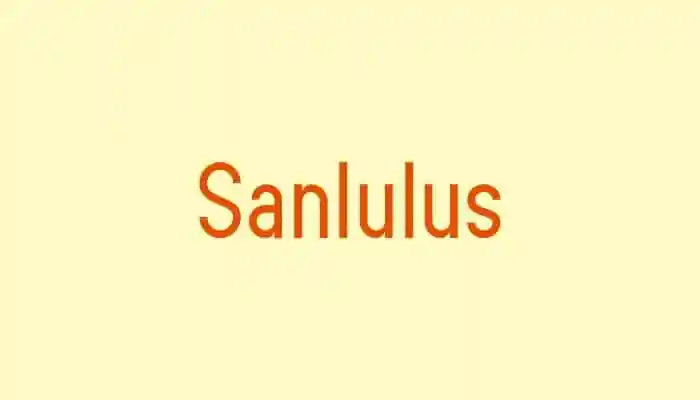
Sanlulus Sans Serif é uma fonte moderna e clean que oferece um toque industrial distintivo sem perder sua simplicidade pura. Suas linhas leves e a arquitetura neutra permitem uma ampla gama de possibilidades para qualquer aplicação visual, seja como logomarca, headlines impactantes, títulos expressivos, capas de revistas ou até mesmo cartazes que desejam fazer um forte impacto. Ideal para os designers que buscam uma fonte sólida e versátil, Sanlulus se torna a escolha perfeita para qualquer projeto que precise expressar determinação e força visualmente. Suave mas inegavelmente aguerrido, esta é uma adição valiosa ao seu arsenal de recursos gráficos.